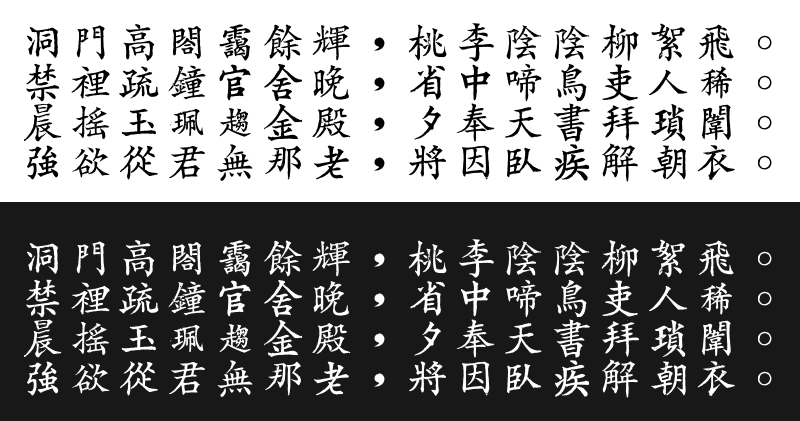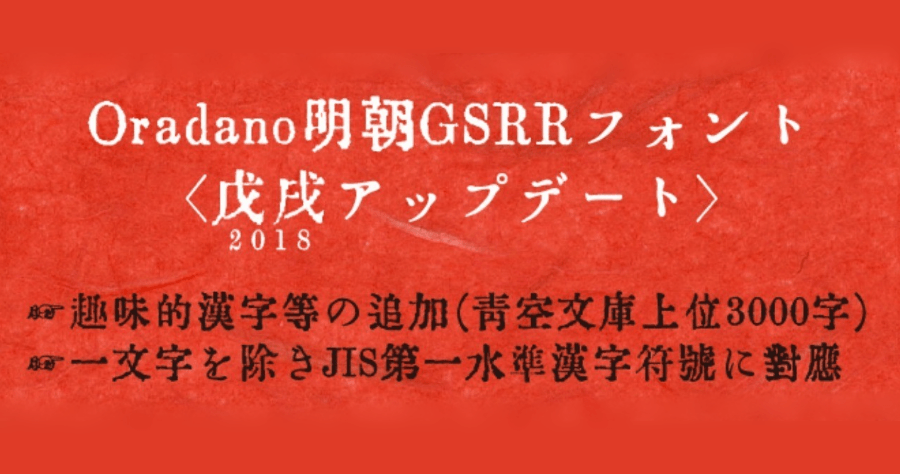
ORADANO Mincho 明朝日文字型免費可商用下載!重回活版印刷的鉛字之美
你在尋找有復古感的中文字體嗎?最近小編發現 ORADANO Mincho 明朝日文字型,字體風格有強烈的鉛字印刷感,字體為明治 30 年東京築地販售的「活版印刷字型」為基礎,讓大家可以回顧明治時代的懷舊風,雖然它是日文字體,不過日積月累更新下來,目前明朝日文字型漢字已超過 3000 個,字體授權為公眾領域授權,部分字體可提供免費、個人商業使用,有需要的朋友趕緊收下啦。它有另一款兄弟字體「恐怖明朝字型」,專門用在製造恐怖氛圍的情境上,有需要的朋友可以一起收下唷。
上圖是小編用 ORADANO Mincho 試打文字呈現出來的效果,「哇哇」這兩個字就缺字,小編用拼字拼出來的,除此之外其它字都是原本就有的,所以支援超過 3000 漢字依然會有部分缺字的問題,不過整體來說活版印刷字體的效果相當不錯,小編把載點放在下方,有需要的朋友趕緊收下啦。